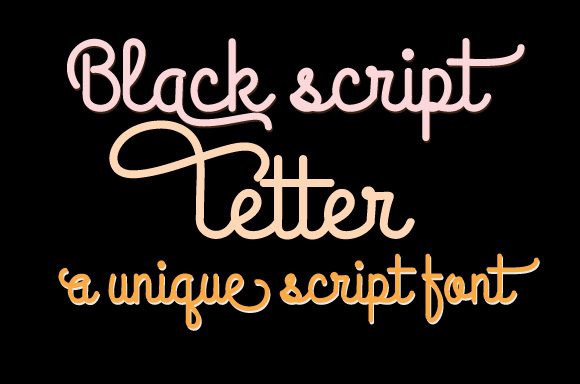
Black Script Letter
適切なデザイン要素を見つけるのは難しい場合がありますが、Black Script Letterは作品を即座に引き立てる優れたコレクションを提供します。
精密に作られたBlack Script Letterは、クリーンなベクター、滑らかなタイポグラフィ、そして安心のための商用ライセンスを提供します。
POD(オンデマンド印刷)製品、結婚式の招待状、またはソーシャルメディアのグラフィックを作成している場合でも、Black Script Letterは理想的です。